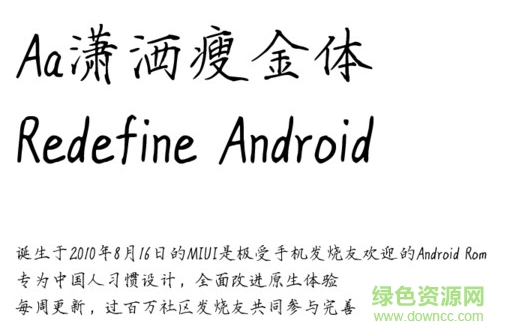
瀟灑瘦金體是一款很有魏晉豐富的瘦金字體,行筆流暢不失承轉(zhuǎn)合之美,字體灑脫延續(xù)魏晉飄逸之風,喜歡的朋友就來綠色資源網(wǎng)收藏吧!
瘦金體運筆靈動快捷,筆跡瘦勁,至瘦而不失其肉,其大字尤可見風姿綽約處。因其筆畫相對瘦硬,故筆法外露,可明顯見到運轉(zhuǎn)提頓等運筆痕跡,是一種風格相當獨特的字體。
宋徽宗的書法筆畫瘦硬,初習黃庭堅,后又學褚遂良和薛稷、薛曜兄弟,并雜糅各家,取眾人所長且獨出己意,最終創(chuàng)造出別具一格的“瘦金書”體,影響頗大。
瘦金書是一種風格相當獨特的字體。此書體以形象論,本應(yīng)為“瘦筋體”。以“金”易“筋”,是對御書的尊重。這是一種非常成熟的書體,趙佶已把它的藝術(shù)個性發(fā)揮得淋漓盡致。這種瘦挺爽利、側(cè)鋒如蘭竹的書體,是需要極高的書法功力和涵養(yǎng),以及神閑氣定的心境來完成的。